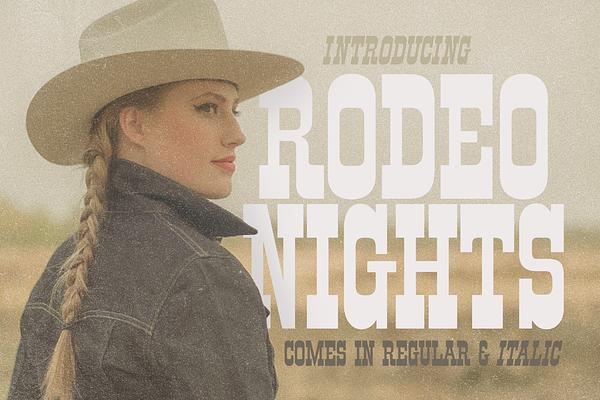
西部牛仔风 Rodeo Nights 字体
Rodeo Nights - Western Font
画面中一位戴着牛仔帽、梳着麻花辫的女性侧脸,背景为朦胧的荒野,整体呈现复古西部风格。字体为粗犷的西部牛仔风格,白色大字叠加在画面中央,搭配暖黄色调和颗粒质感,适合用于海报、品牌标志、标题设计等需要展现粗犷、复古西部氛围的场景。